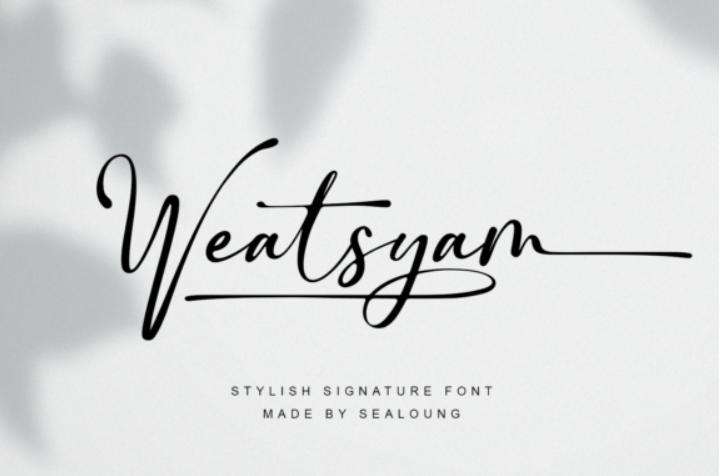
[Creativefabrica] Weatsyam Font (Sealoung)
Weatsyam - уникальный и элегантный рукописный шрифт. Он прекрасно смотрится на различных дизайнах, требующих индивидуального стиля, таких как свадебные приглашения, открытки с благодарностью, свадьбы, поздравительные открытки, логотипы и так далее.